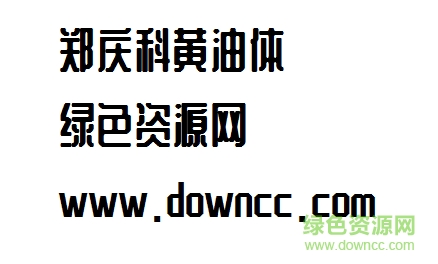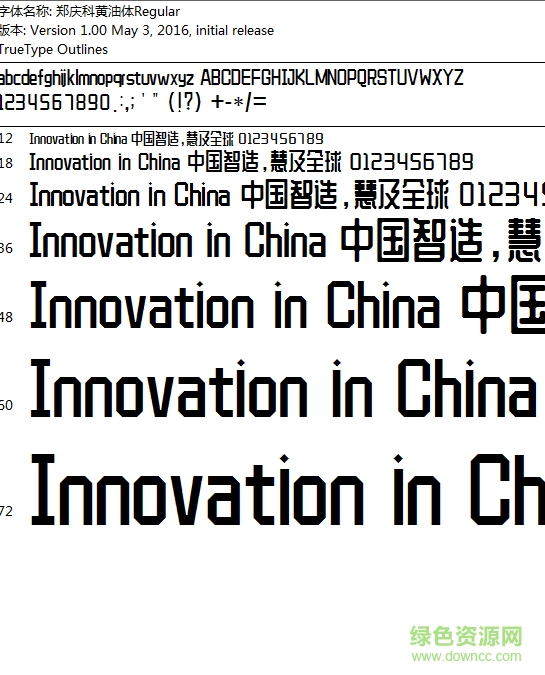
鄭慶科黃油體字體
鄭慶科黃油體是一款以著名書法家鄭慶科為背景的中英文字體軟件,該字體粗黑正式感強(qiáng),在海報(bào)廣告的標(biāo)題設(shè)計(jì)上有不錯(cuò)的應(yīng)用,綠色資源網(wǎng)為您提供免費(fèi)字體下載!
可愛(ài)的黃油體,適用于店招、banner、標(biāo)志、等領(lǐng)域,綠色資源網(wǎng)為您提供免費(fèi)下載使用!